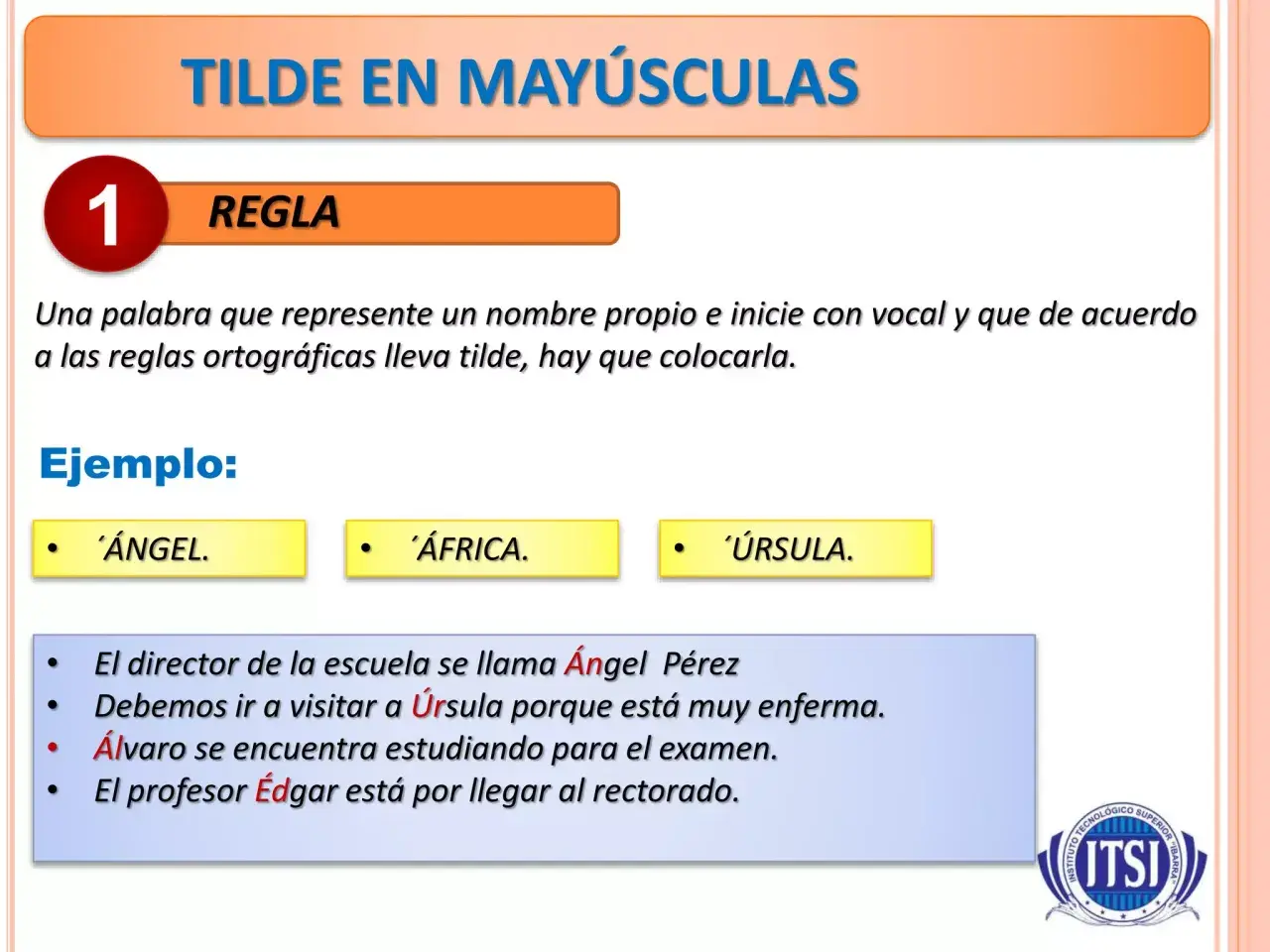
La I mayúscula en tipografía - cómo se escribe y cuándo lleva tilde
Regla de tilde en mayúsculas: nombres propios como Ángel, África y Úrsula llevan tilde.
La I mayúscula parece una letra mínima, pero en tipografía resuelve más de lo que parece: aclara textos, evita confusiones con la l y el 1, y cambia bastante según la fuente, el soporte y la intención visual. Aquí verás cómo se escribe, cuándo lleva tilde, en qué contextos aparece y qué conviene cuidar si trabajas con letras, rótulos o composiciones tipográficas.
Lo esencial de la I mayúscula en una mirada rápida
• La mayúscula de la i es I, y en español normal no lleva punto.
• Si la vocal lleva tilde, la forma correcta es Í.
• Su dibujo cambia mucho según la tipografía: puede ser un asta simple o una letra con remates.
• Se usa sobre todo en nombres propios, siglas y números romanos.
• En diseño conviene vigilarla porque se confunde con l y 1 con mucha facilidad.
Qué es la I mayúscula y por qué importa tanto en español
La I mayúscula es la forma capital de la letra i, y en la escritura habitual del español funciona como cualquier otra mayúscula inicial: abre nombres propios, aparece en siglas y se integra en textos en versales o en mayúsculas completas. La RAE recuerda un detalle que suele pasarse por alto: la forma mayúscula de i y j carece de punto. En manuscrita, muchas personas lo añaden para mejorar la lectura cuando el trazo es muy simple, pero en imprenta y en tipografía digital no hace falta.
También conviene separar dos cosas que a menudo se mezclan: la letra base y la tilde. Si la palabra lleva acento, la mayúscula correcta no es I, sino Í. Ese matiz importa en nombres como Íñigo o en titulares donde la acentuación no desaparece por el hecho de escribir en mayúsculas. Yo suelo insistir en este punto porque en carteles, formularios y piezas decorativas un error tan pequeño se nota mucho. Y, precisamente por eso, la forma visual de la letra merece un vistazo más atento.
Cómo cambia la I según la tipografía y el soporte
La I mayúscula no siempre se dibuja igual. En una tipografía serif puede tener remates arriba y abajo, mientras que en una sans serif suele verse como un asta vertical limpia, casi sin adornos. En una fuente display puede ganar presencia, espesor o gestos más decorativos, y en caligrafía puede adoptar un trazo más expresivo. El carácter es el mismo, pero el glifo, es decir, la forma concreta que dibuja la fuente, cambia por completo.
Esto importa mucho en diseño porque la I es una letra muy visible y, al mismo tiempo, muy fácil de confundir. En una pantalla, una I muy fina se pierde antes que otras letras; en un rótulo pequeño, una I demasiado minimalista acaba pareciendo un palito sin identidad. En Unicode, la I mayúscula corresponde a U+0049, pero ese código no dice nada sobre su aspecto: el dibujo depende de la fuente que elijas.
Estilo tipográfico Cómo suele verse la I Dónde funciona mejor Riesgo habitual
Serif Con remates visibles arriba y abajo Editorial, invitaciones, textos con aire clásico En tamaños pequeños puede perder nitidez
Sans serif Asta limpia y más geométrica Interfaces, señalética, textos modernos Se confunde con l o 1 si la fuente es demasiado neutra
Display Más carácter, contraste o gestos decorativos Títulos, portadas, branding La forma puede volverse más expresiva que legible
Caligráfica Trazo manual, a veces con variación de grosor Lettering, papelería, artesanía Si el trazo es demasiado simple, desaparece entre otras letras
Cuando trabajo con letras, me fijo menos en si la I es bonita y más en si se lee sin esfuerzo. Esa diferencia parece obvia, pero no lo es: una I muy elegante puede fallar justo donde más la necesitas, que es en tamaños pequeños o en composiciones densas. Y ahí entra el uso real de la letra en textos normales.
Cuándo aparece en textos reales
La I mayúscula no vive solo en ejemplos escolares. En español aparece en nombres propios, en siglas, en numeración romana y en textos que usan versales para dar jerarquía o énfasis. Además, cuando una palabra lleva tilde, la mayúscula la conserva. Omitirla no es una decisión de estilo: es un error ortográfico.
Contexto Ejemplo Qué conviene vigilar
Nombre propio Inés, Íñigo La tilde se mantiene en la mayúscula cuando corresponde.
Sigla o abreviación IES, I+D La I puede formar parte de la forma completa o de la sigla.
Número romano Luis I, capítulo IV, siglo XXI Aquí la I funciona como número, no como vocal.
Texto en mayúsculas HIJO, IMPRENTA, ÍNDICE La ausencia de punto evita ruido visual y la tilde no debe desaparecer.
En la práctica, el problema no suele ser la norma, sino la prisa: se escribe en mayúsculas y alguien borra la tilde porque piensa que “ya no hace falta”, o cambia una I por una i minúscula porque visualmente queda mejor. Ninguna de esas soluciones ayuda. La letra correcta existe, solo hay que respetarla y dejarla respirar. Eso nos lleva a la parte más delicada para quien diseña o maqueta: distinguir bien letras y números que se parecen demasiado.